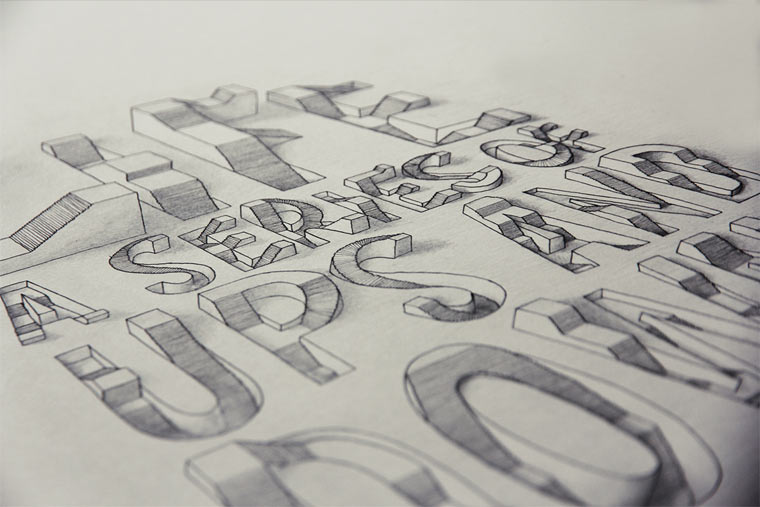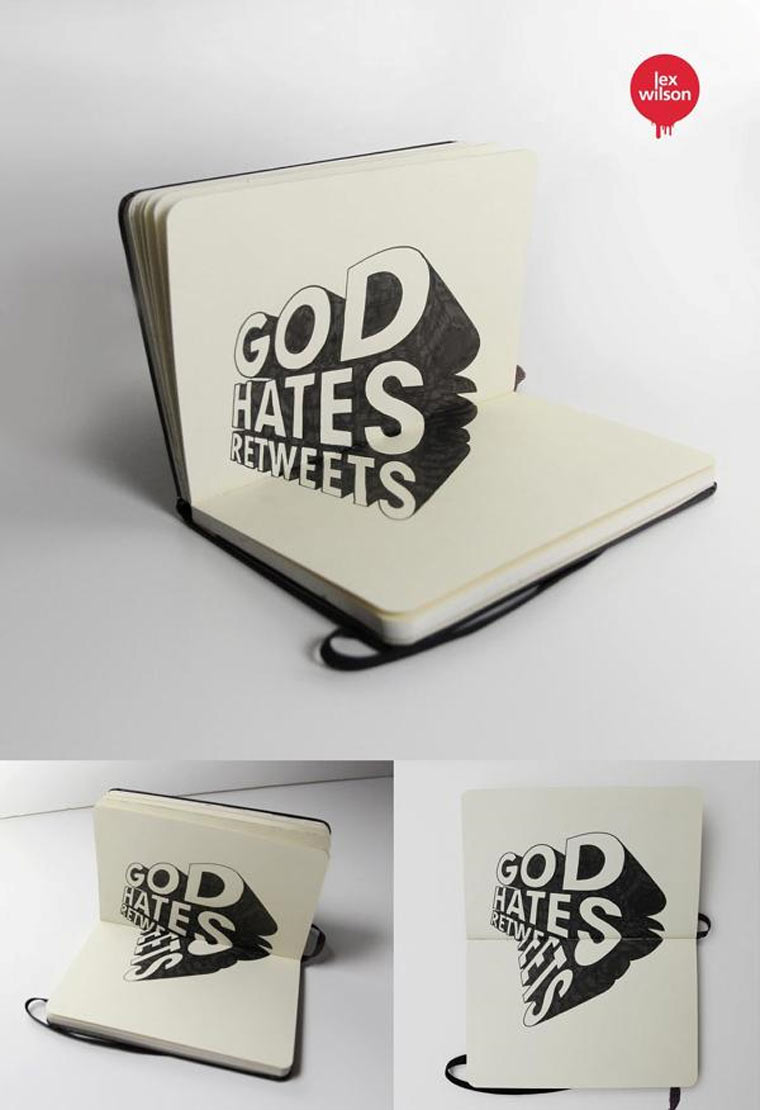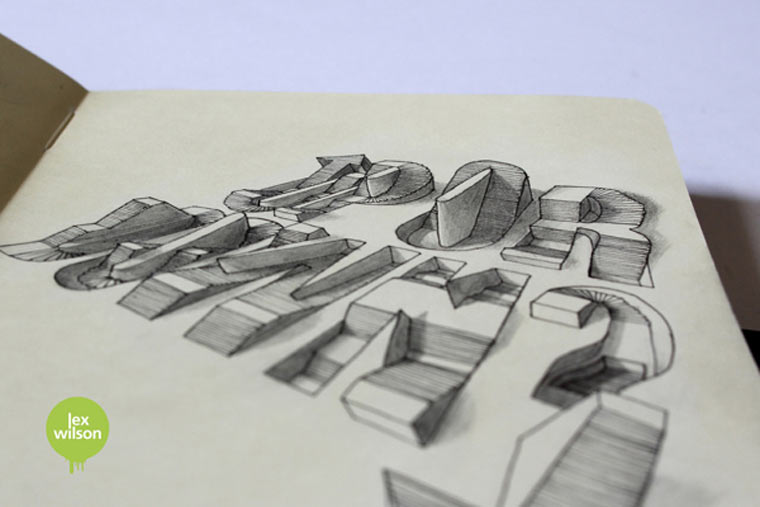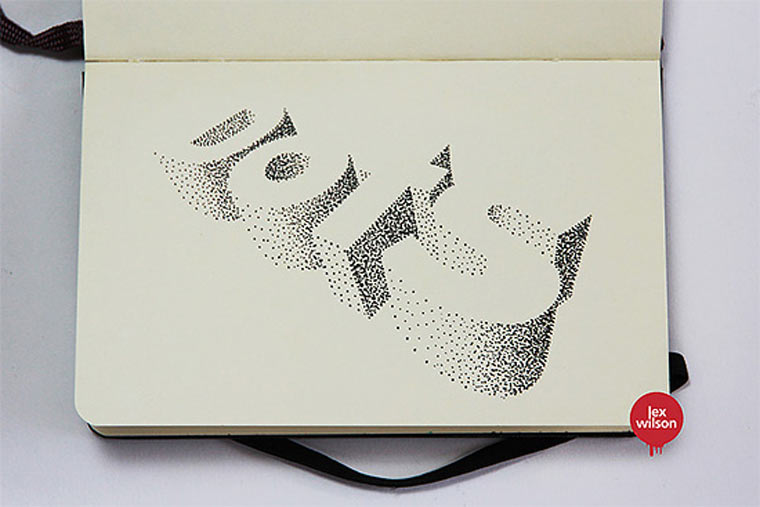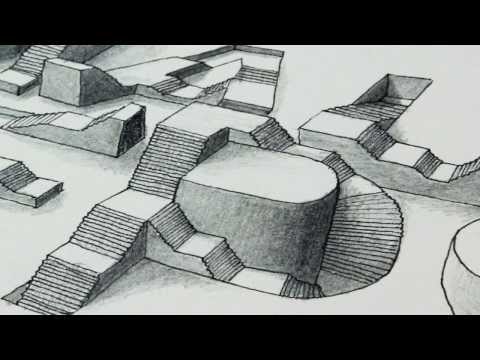
Zeichnungen vom Allerfeinsten
3D-Typografie von Lex Wilson
Illustrator Lex Wilson aus London schafft es, Worten kreativ Ausdruck zu verleihen, indem er sie bspw. in der Form gestaltet, was sie selbst sind/aussagen. „Dots“ besteht dann eben aus Punkten und ein „Life – a series of ups and downs“ wird dann eben dreidimensional dargestellt. Aber nicht einfach plump mit einem Fluchtpunkt, sondern fein ausgegliederte Typografie und alles andere als langweilig.
3D typography Illusion - "Small Steps"